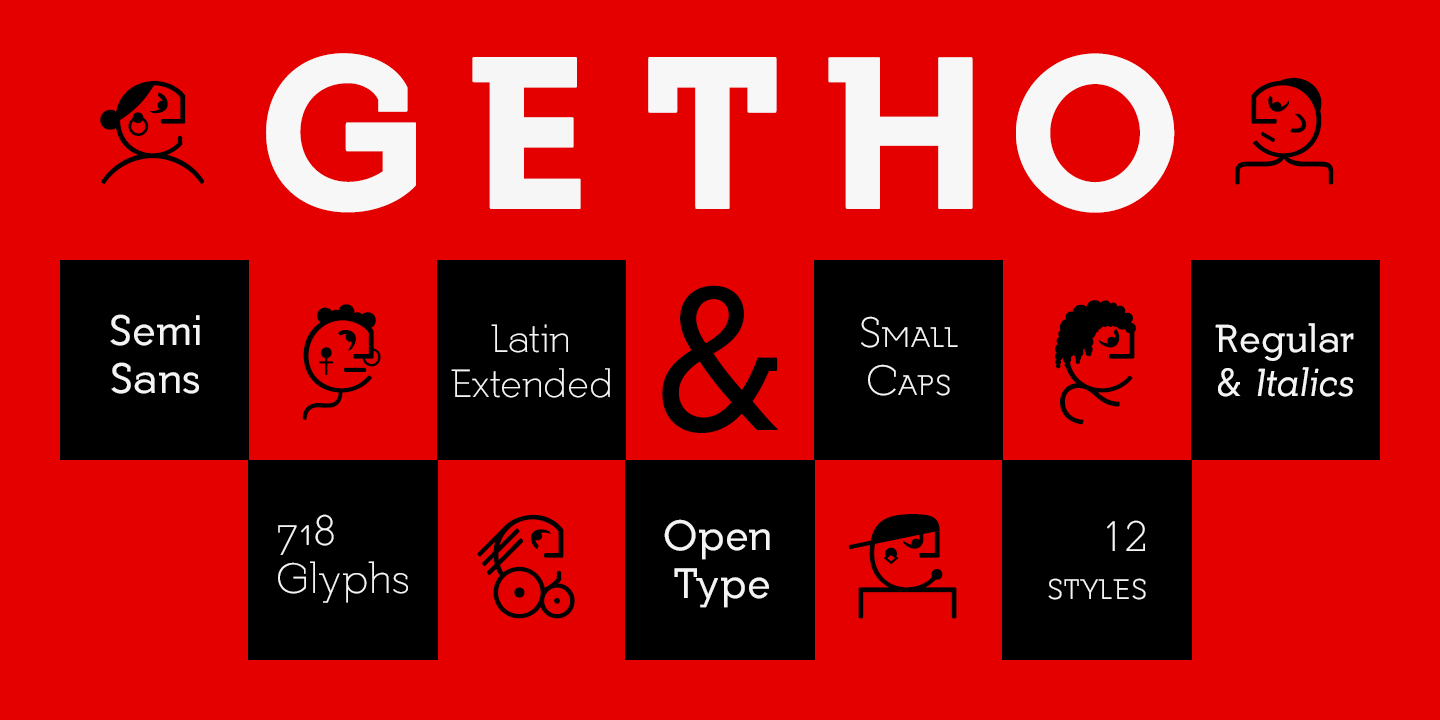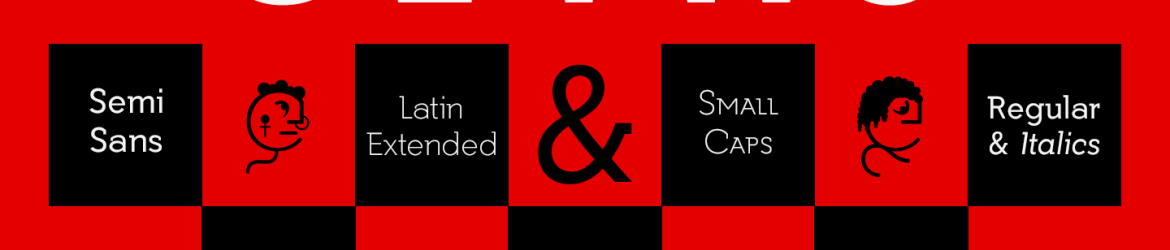
A Getho é uma família de fontes geométricas de Semi Sans que incorpora elementos de construção, com 6 pesos diferentes e versões itálicas incluídas, todas elas contendo minúsculas. Esta famosa fonte é conhecida por ser um símbolo do Bitcoin e outros símbolos monetários, mas sua simplicidade geométrica oferece uma elegância única que se sobressai além da especificação de seu uso. Seja para aplicações digitais ou impressas, a Getho Semi Sans é perfeita para dar um toque moderno e único ao design de qualquer projeto. Suas linhas retas e formas geométricas criam uma aparência que se destaca em qualquer fonte combinada, tornando-a uma escolha popular entre designers e gráficos digitais.